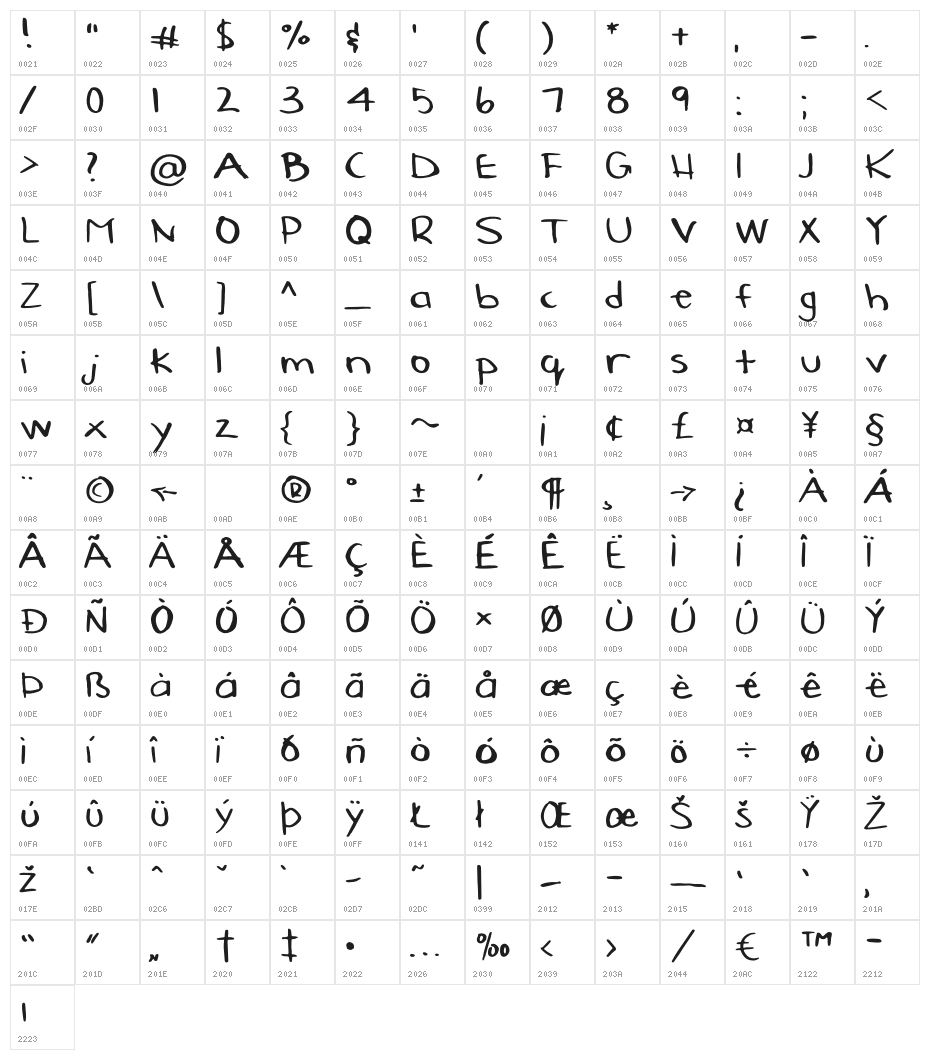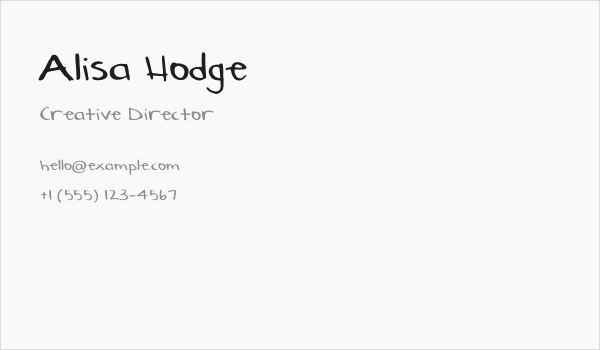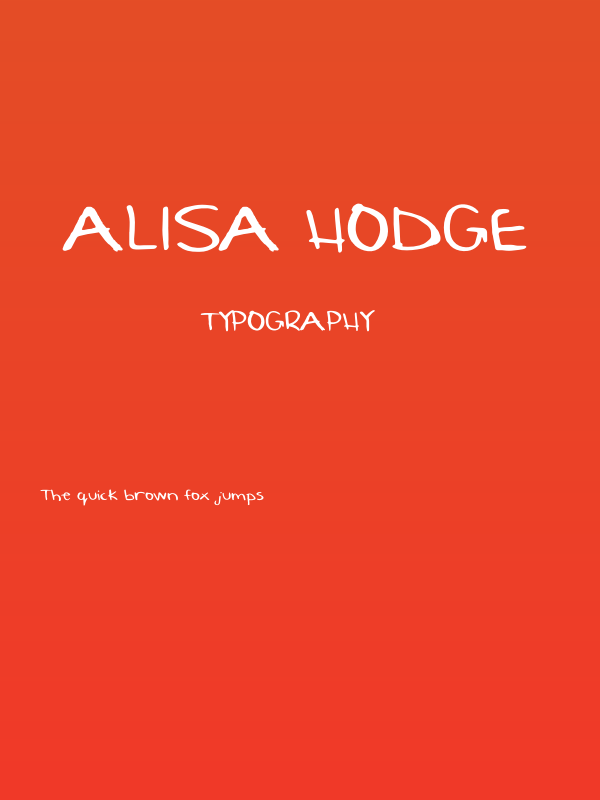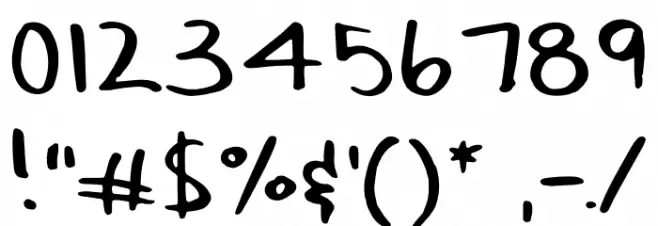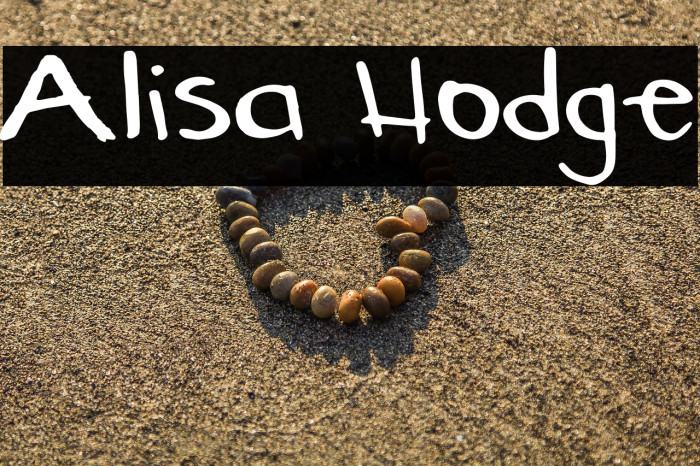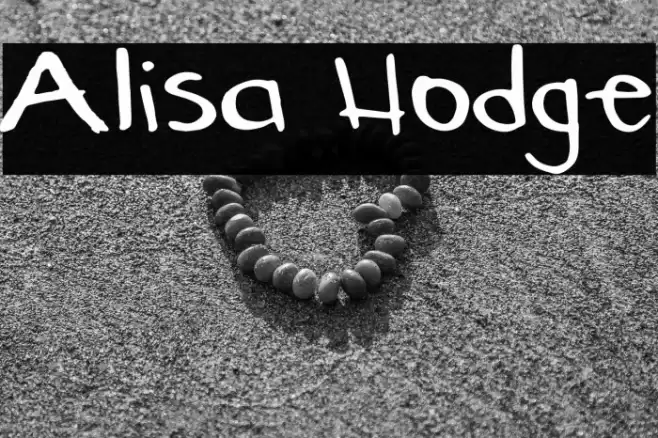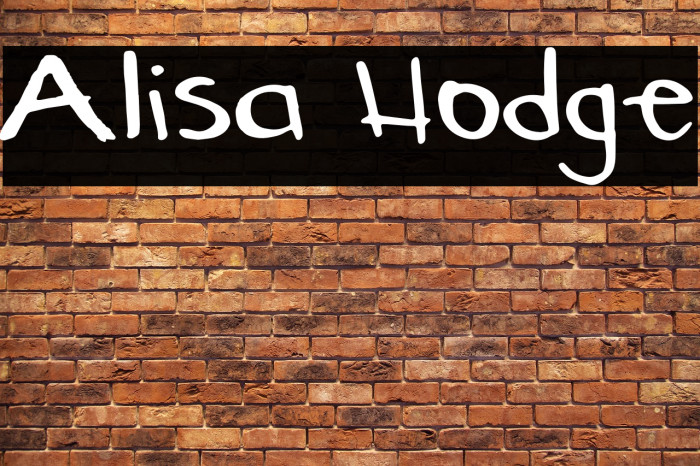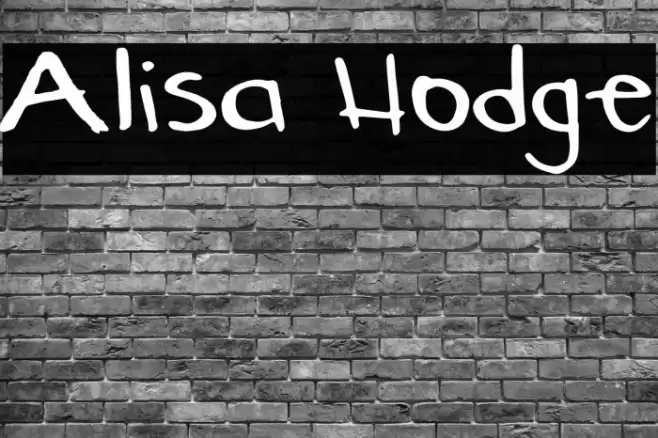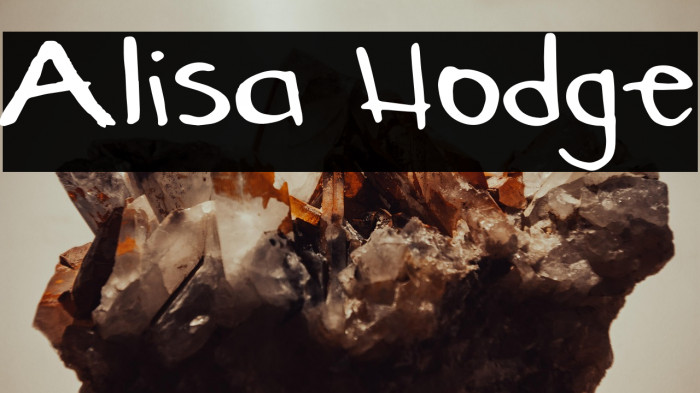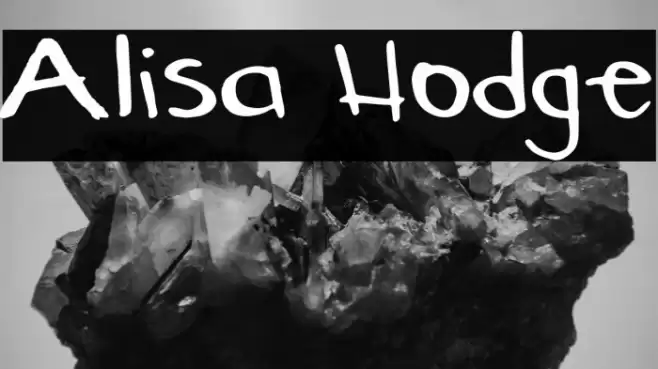
Alisa Hodge Font
| Gesamtstil | Casual, Playful |
| Anwendungsfall | Headlines, Informal text, Creative projects |
| Vorgeschlagene Projekte | Ideal for children's books, greeting cards, casual branding, and social media graphics. |